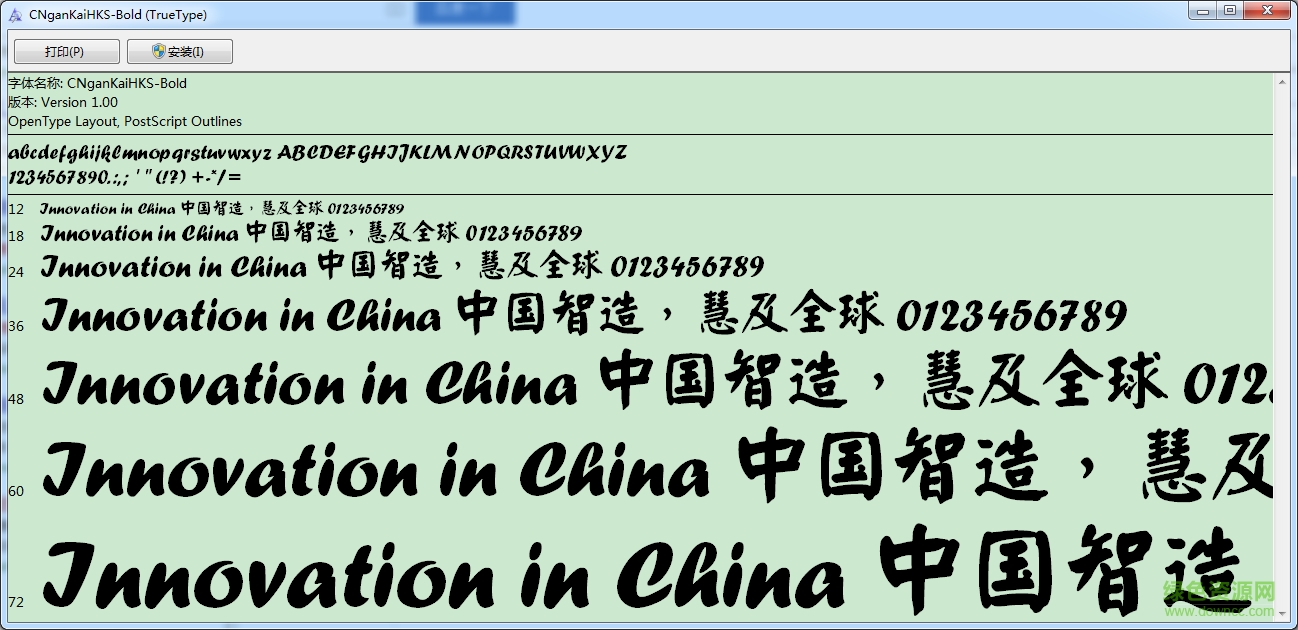
軟件介紹 軟件標簽: 蒙納字體 字體 蒙納簡顏楷體是一款非常漂亮的簡體字體,這款字體大氣沉穩(wěn),筆畫上處理精致得當,十分美觀,整體效果非常出色,比較適用于廣告設計、美術設計等領域。喜歡這款自提的朋友歡迎來綠色資源網下載使用!蒙納簡顏楷體安裝方法方法一:控制面板/字體/文件/安裝新字體;方法二:直接將字體復制到C:\WINDOWS\Fonts。方法三:針對win7系統(tǒng),用戶只需選中字體右鍵安裝即可。溫馨提示本站所有字體資源僅供個人學習與參考,如需商業(yè)使用請到相關官網授權! 軟件截圖 上一張下一張(1 / 1) 安裝詳細截圖 猜你喜歡 顏體字體 楷書字體 顏體字體 顏體是一款極具古樸厚重韻味的字體,這里匯集了各具特色的顏體字體,每款字體都有著顏體豐腴雄渾、骨力遒勁的魅力,因此顏體也深受廣大書法家的喜愛,下面有綠色資源網小編為大家提供顏體字體下載大全,感興趣的朋友歡迎來綠色資源網下載體驗! 查看更多>> 經典簡顏體字體 2.44M/中文/1.2/下載 tianshi-yanti字體 2.92M/中文/5.0/下載 全真顏體簡體字體 4.88M/中文/2.5/下載 fashionfont052 by字體 2.44M/中文/2.0/下載 刻石錄顏體字體 8.53M/中文/5.7/下載 顏體字體下載大全 52.01M/中文/1.6/ttf下載 楷書字體 楷書字體是綠色資源網小編專為大家收集的一類非常流行而且好用的楷書字體,它包括了各種形式的楷書??瑫步姓⒄鏁?、正書。從程邈創(chuàng)立的隸書逐漸演變而來,更趨簡化,橫平豎直,筆勢雄奇,姿態(tài)橫生,可應用于繪畫設計、藝術創(chuàng)作、平面廣告、印刷包裝、電視廣告等等各行各業(yè)。也是現(xiàn)在很多行業(yè)必用的一類字體,小編收集的這一類楷書字體希望能更好的幫助大家收集和使用楷書字體。 查看更多>> 楷體國標字體官方版 2.45M/中文/7.1/下載 漢儀閃耀楷書字體 1.77M/中文/0.0/下載 華為漢儀錦時楷書 2.92M/中文/5.0/下載 楷書字典手機版 4.46M/中文/5.0/v2.0 安卓版下載 經典楷體繁體 3.96M/中文/5.0/下載 楷書繁體字體包 9.76M/中文/8.0/下載 其他版本下載 標題 大小 更新日期 下載 下載地址 電腦版 蒙納簡顏楷體字體 ttf版 點擊報錯 軟件無法下載或下載后無法使用,請點擊報錯,謝謝! 關閉報錯反饋 請描述您所遇到的錯誤,我們將盡快予以修正,謝謝! *必填項,請輸入內容 本類最新 mellehks-medium-中常規(guī)體 myounghks-xbold-粗體字體 蒙納簡粗黑字體 mqinghuahks xbold字體 mcutehks light字體 msung 蒙納宋體 相關文章 Photoshop字體安裝使用方法和技巧 如何解決“無法新增字體”問題 Win 7系統(tǒng)安裝字體方法 網頁字體大小設置方法 怎么改網頁字體大小 在Linux系統(tǒng)中安裝字體的幾種方法 windows7字體顯示問題:打開某些程序的時候顯示的是亂碼 用戶評論 熱門評論 最新評論 發(fā)表評論 查看所有評論(0) 昵稱: 請不要評論無意義或臟話,我們所有評論會有人工審核. 字數(shù): 0/500 (您的評論需要經過審核才能顯示)